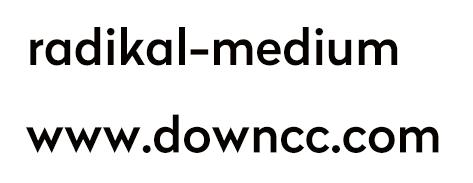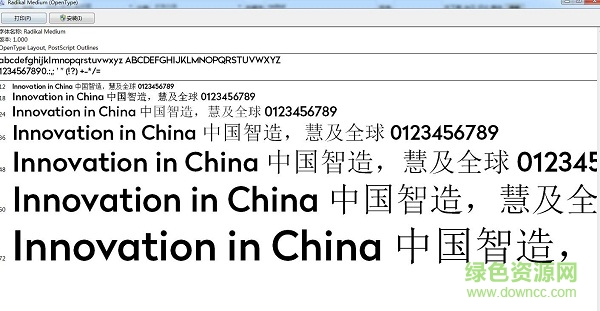
radikal medium字體是一款視覺效果不錯的英文無襯線字體,該字體粗細適中,在網(wǎng)頁設(shè)計方面顯示非常清晰干凈,可以適應廣泛的排印應用,歡迎大家在綠色資源網(wǎng)下載!
1.結(jié)構(gòu)是字體構(gòu)成的法則,以什么法則來組建字體,在字體構(gòu)成中以什么形成字體的個性特色,這都要靠結(jié)構(gòu)來解決。
2.在字體構(gòu)成中,變換結(jié)構(gòu)是體現(xiàn)字體創(chuàng)意表現(xiàn)的主要手法。
3.在字體結(jié)構(gòu)中充分運用形象改變原有的結(jié)構(gòu)風格,能從字體構(gòu)成的本質(zhì)特征上形成突破性個性。